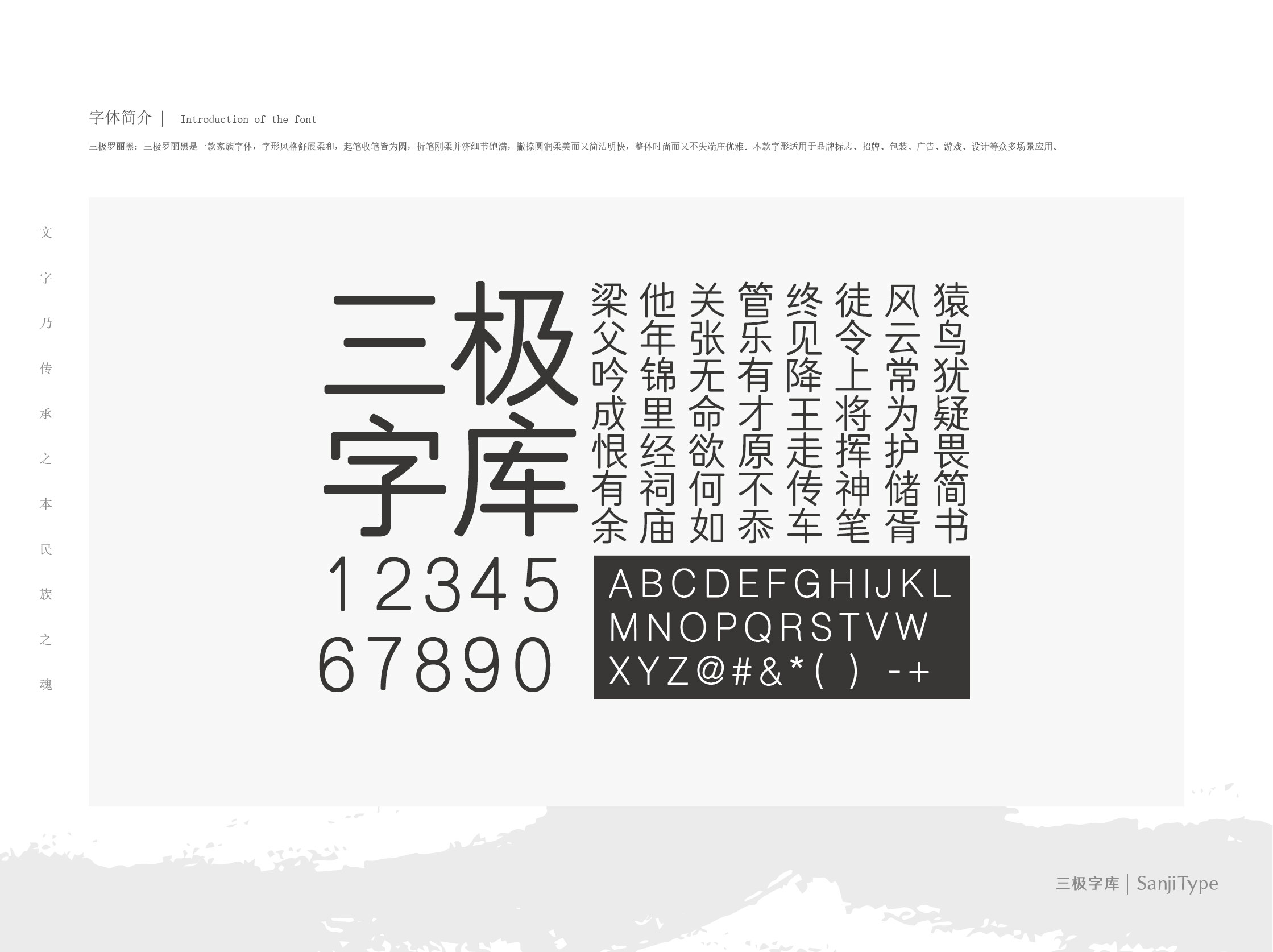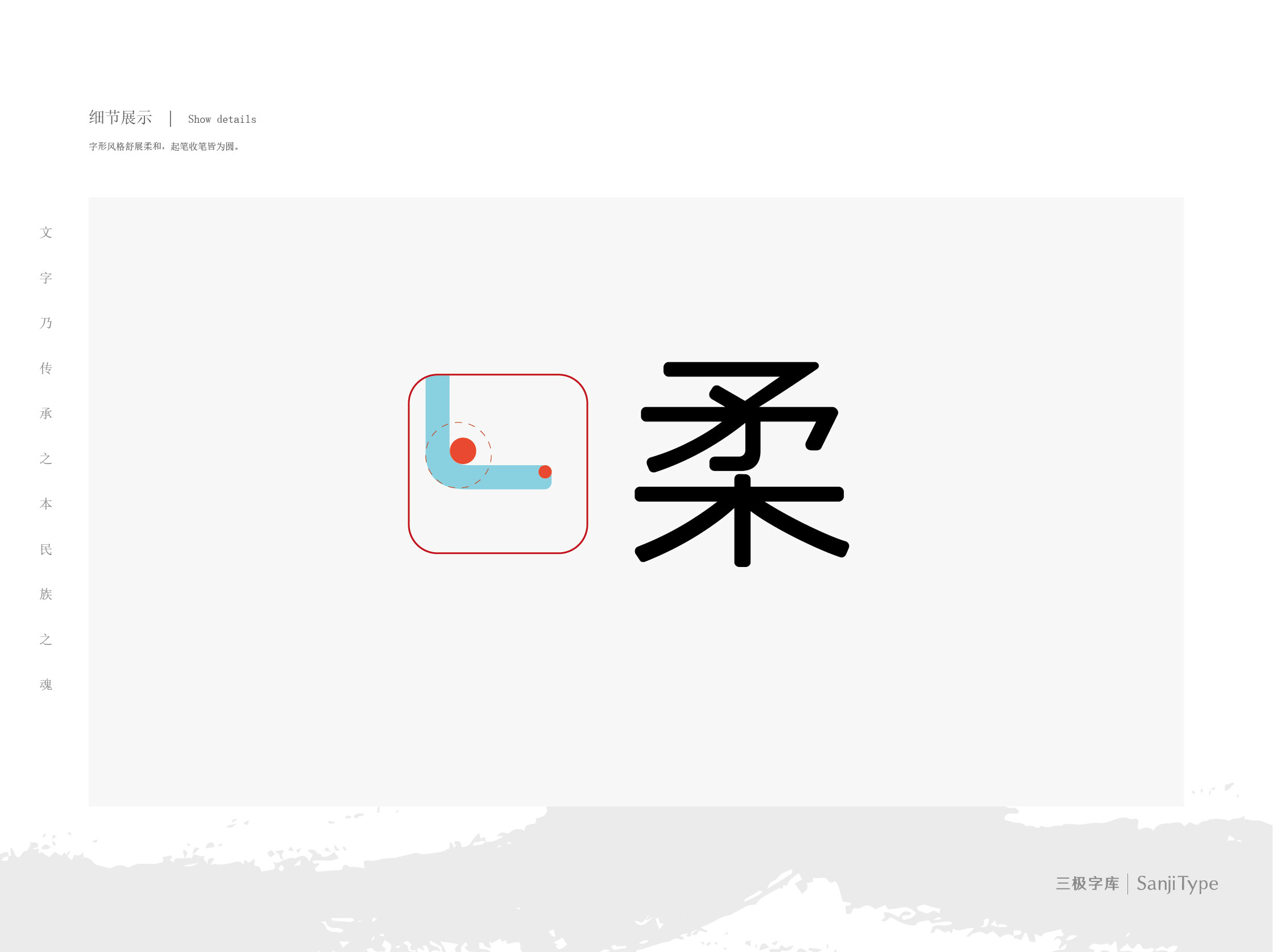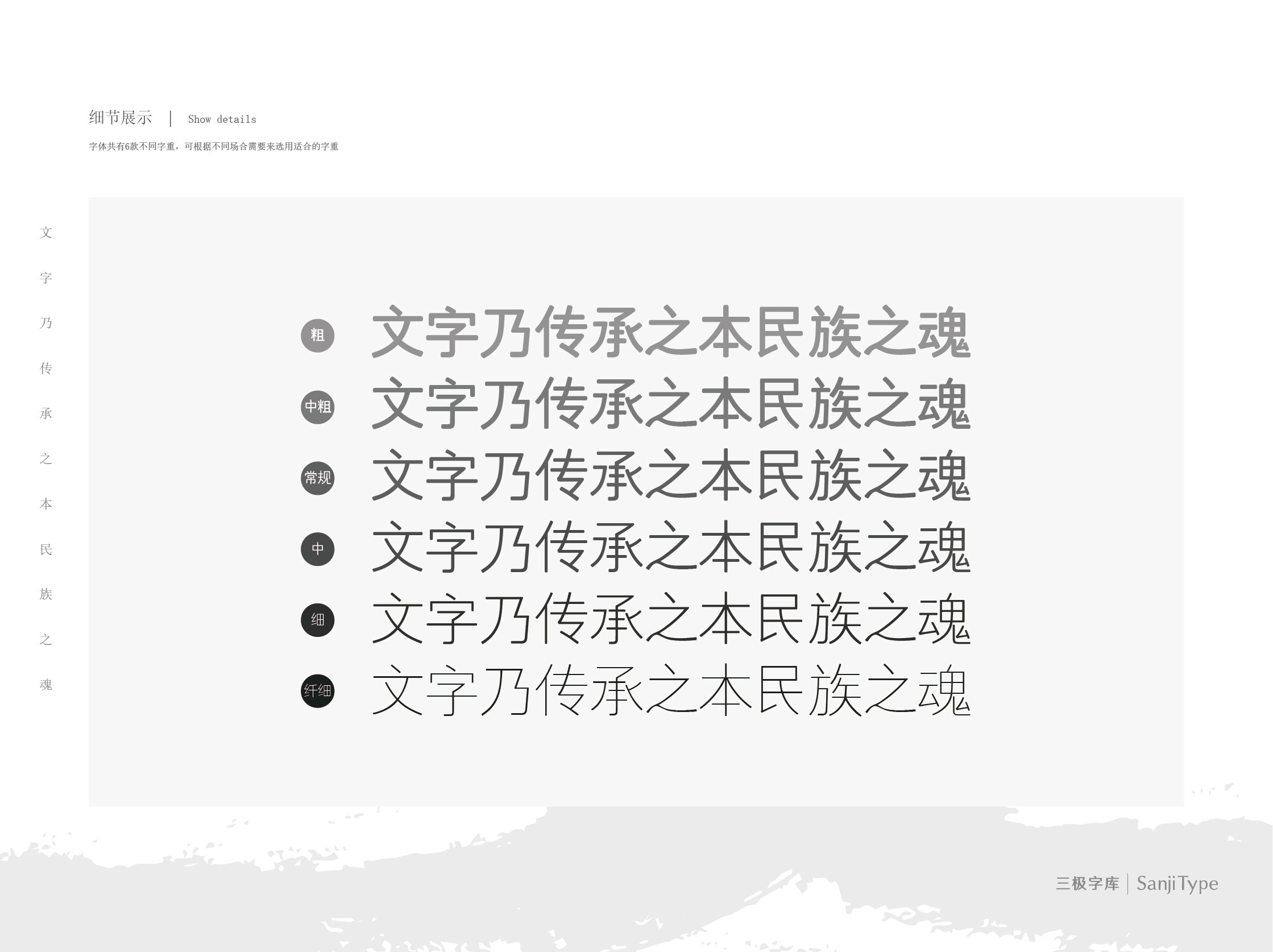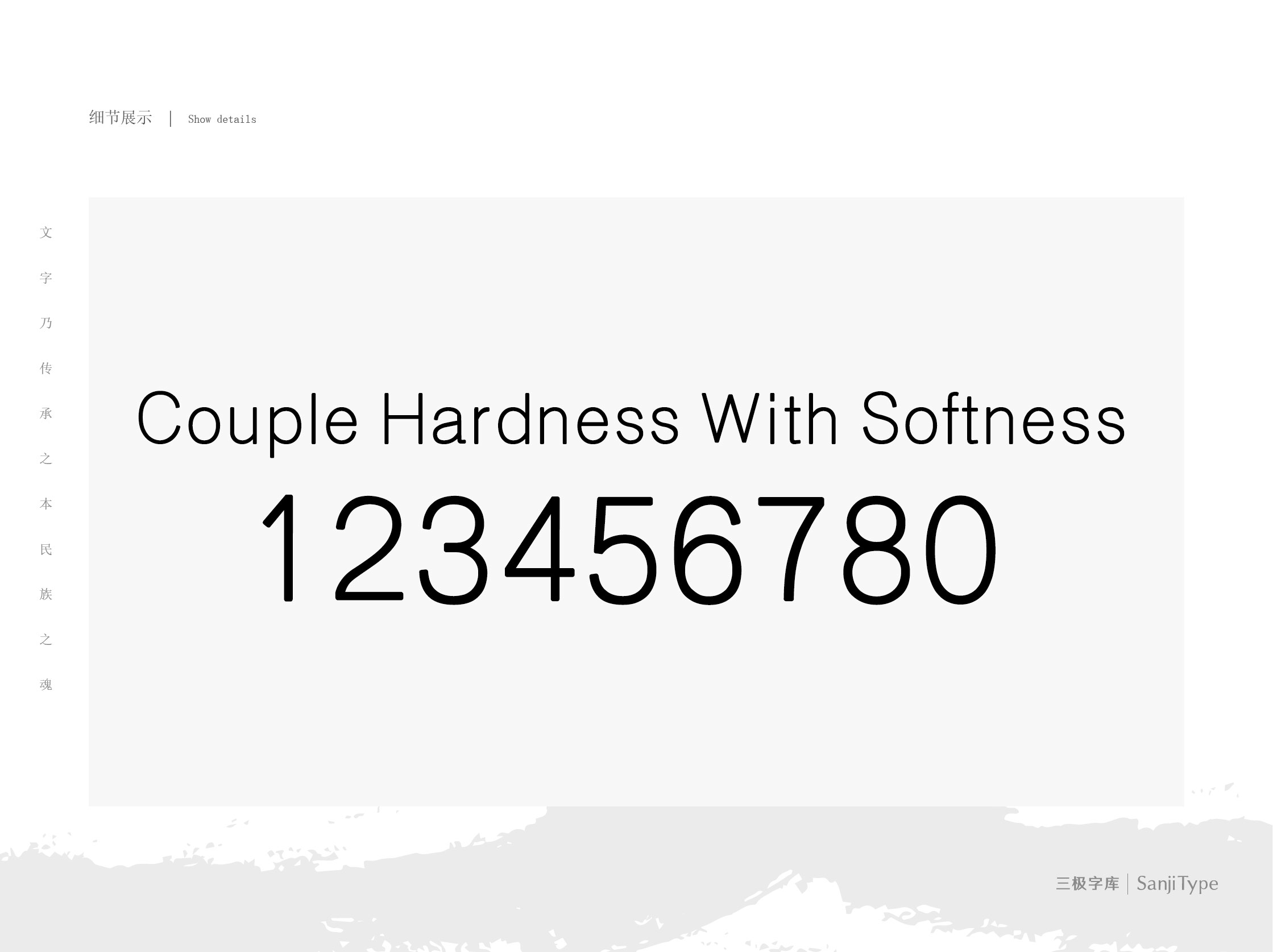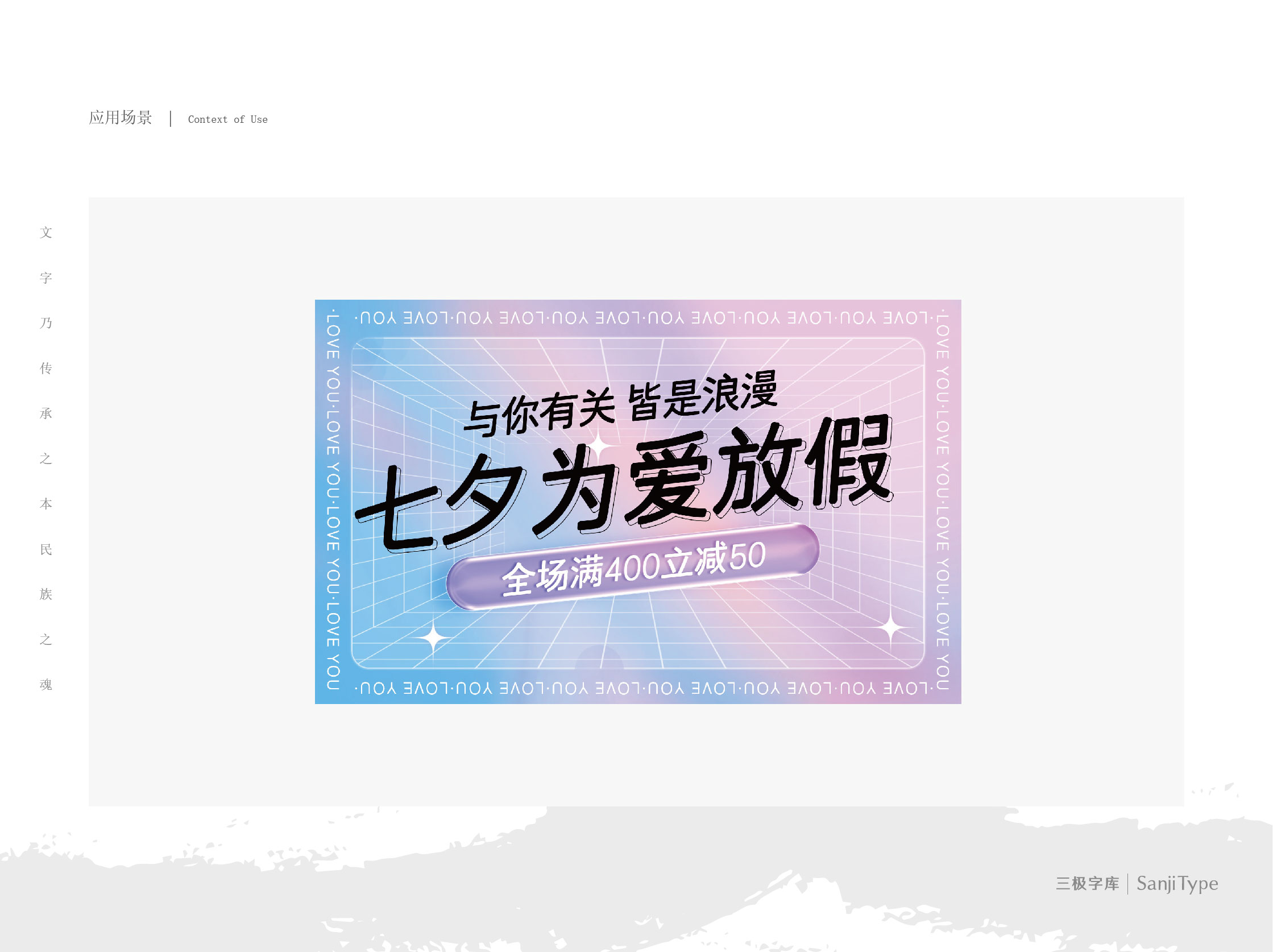
三极罗丽黑家族
三极罗丽黑 纤细
三极罗丽黑 中
三极罗丽黑
三极罗丽黑 中粗
三极罗丽黑 粗
三极罗丽黑 细
罗碧霞 朱文淑 张琼
黑体
三极罗丽黑简体是一款家族字体,起笔收笔皆为圆,折笔刚柔并济细节饱满,撇捺圆润柔美而又简洁明快,整体时尚而又不失端庄优雅。本款字形适用于品牌标志、招牌、包装、广告、游戏、设计等众多场景应用。
同时适用于大众媒介中,如报纸、杂志、书籍、广告、标志、宣传册、空间导视、包装、影视、屏幕显示、交互设计等。